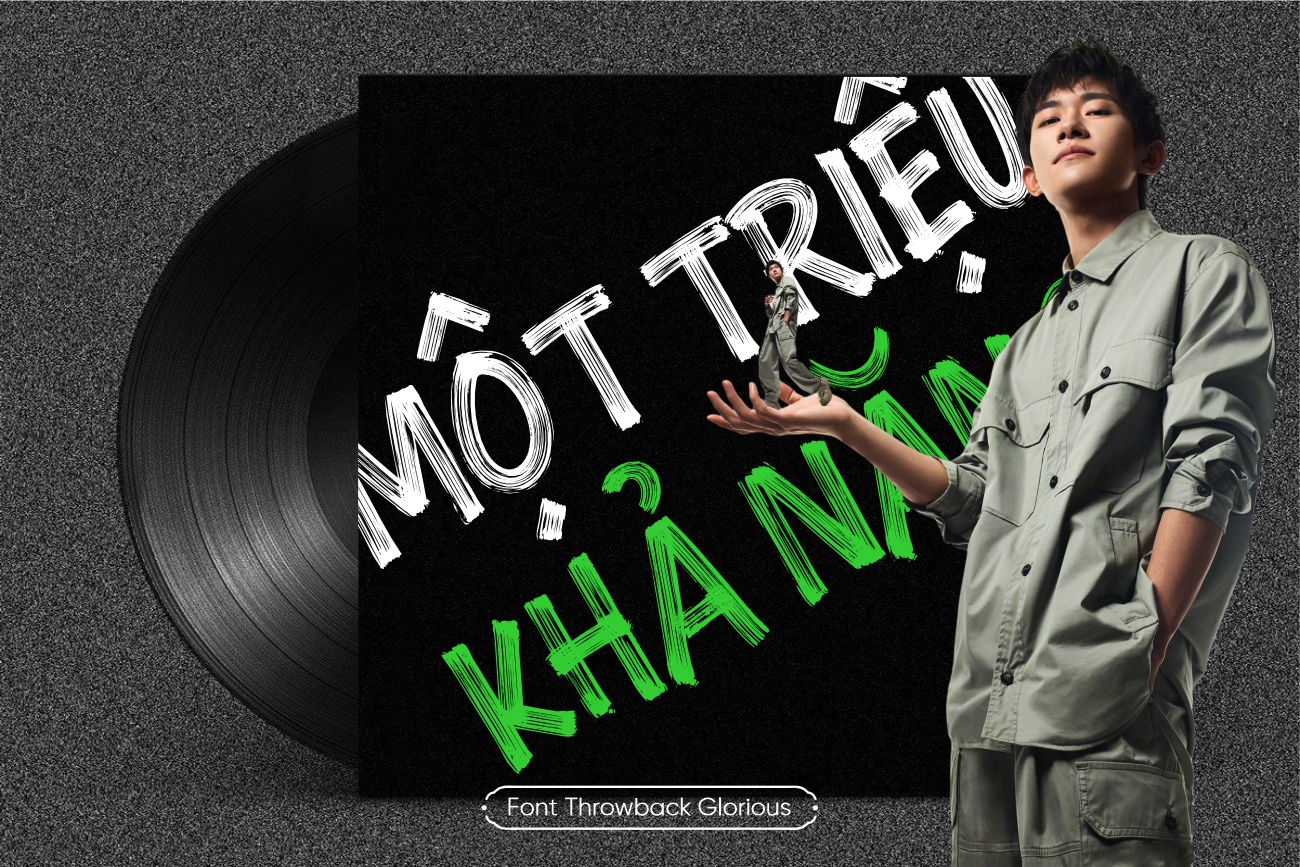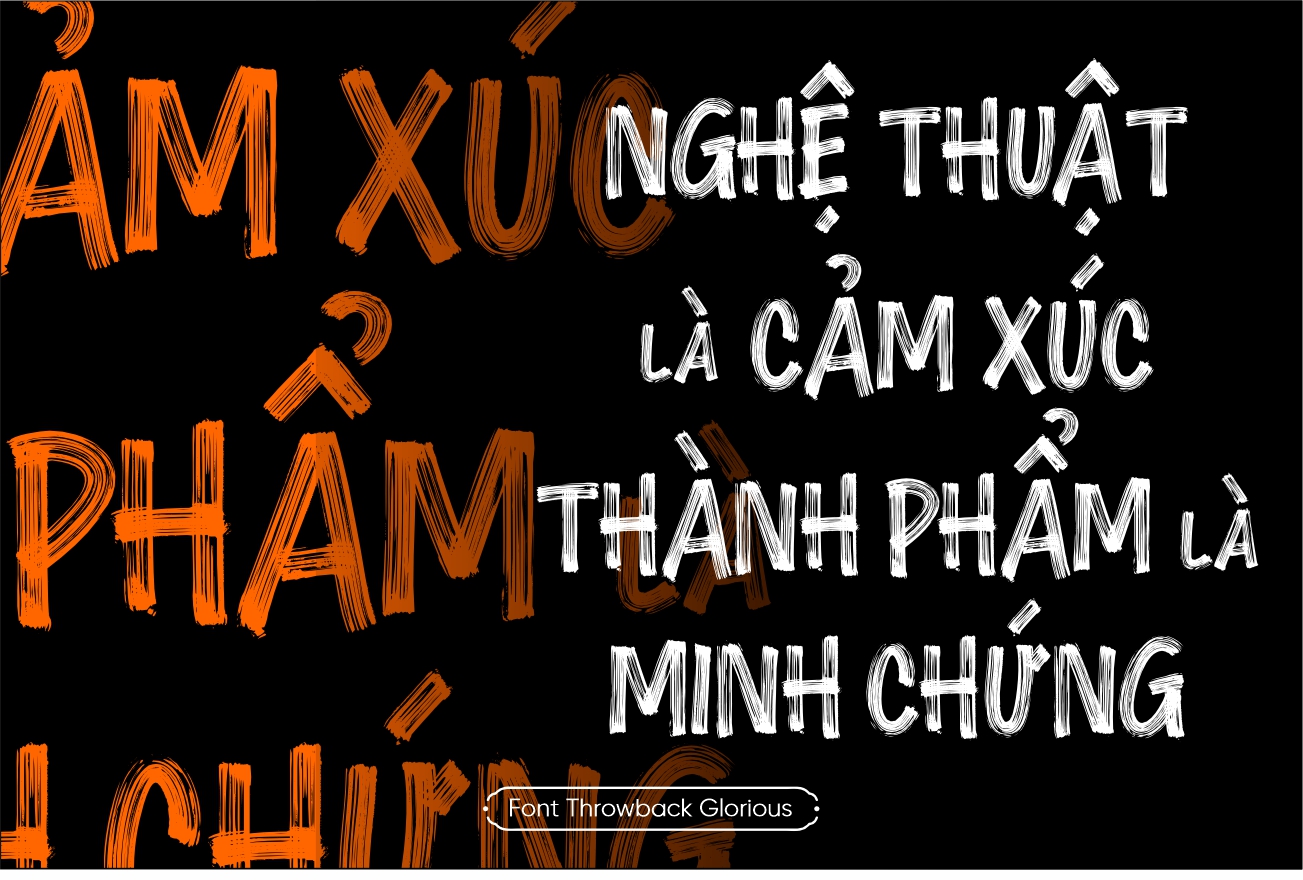
TH Throwback Glorious
Brush
Giới thiệu Font Throwback
Throwback là một kiểu chữ mang phong cách retro kết hợp hiệu ứng cọ vẽ (brush stroke), tạo cảm giác mạnh mẽ, phóng khoáng và đầy năng lượng. Font này đặc biệt phù hợp cho những thiết kế đậm chất hoài cổ nhưng vẫn giữ được sự ngẫu hứng và nghệ thuật.